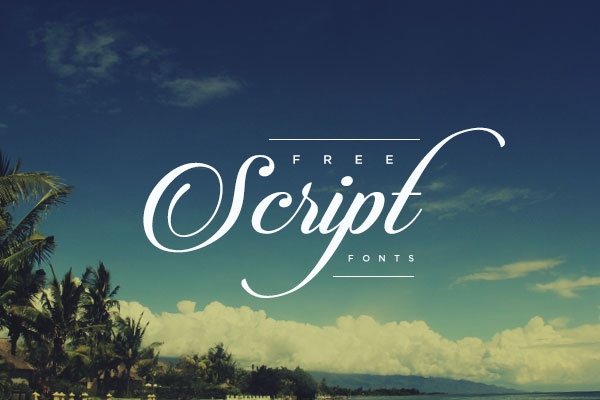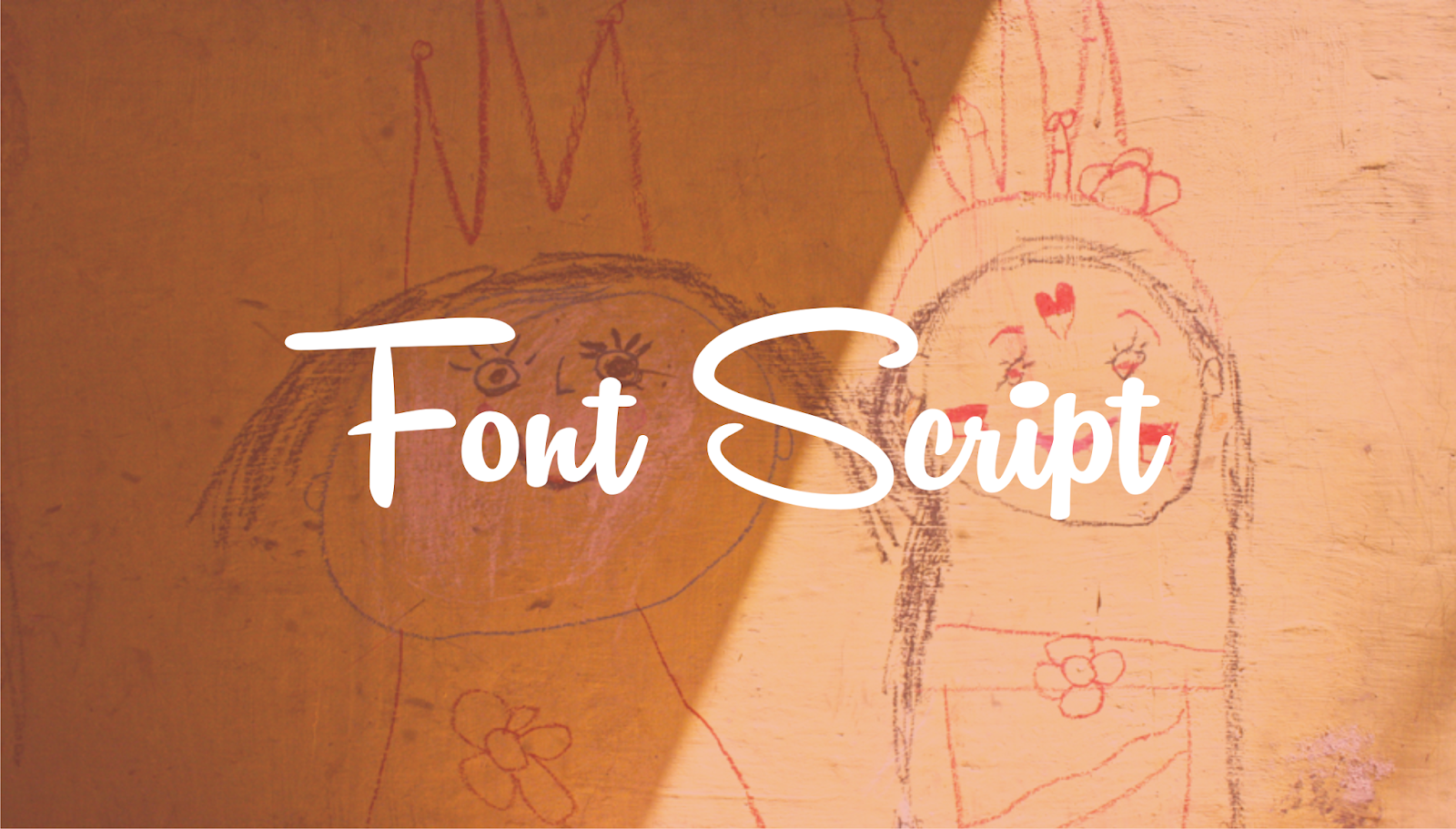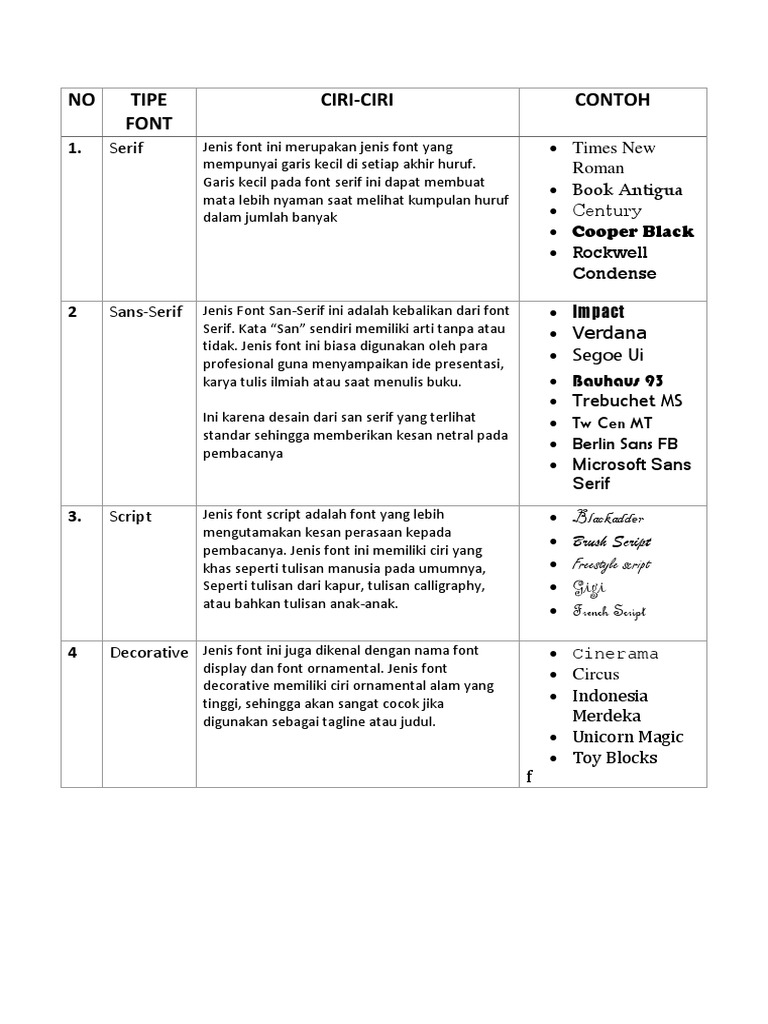
Free Typeface Gothic Merupakan Jenis Font Free Typography Fonts
All Free PSD Mockups - Download Free SVG Cut FilesFont ini memiliki karakteristik huruf kapital yang tidak terlalu tinggi dan terdapat jarat pada setiap hurufnya. Contoh dari font san serif antara lain arial tahoma century gothic dan lain sebagainya. Brooklyn merupakan jenis font yang cukup simpel sederhana terlihat bersih dan teratur.
typeface gothic merupakan jenis font
Typeface gothic merupakan jenis font. 3 script handwriting. Setelahnya anda simpan hasil foto tersebut berupa jpg jpeg atau png. Font secara sederhana typeface bisa disebut sebagai entitas yakni perwajahan karakteristik keunikan dan perbedaan yang terbentuk didalam rancangan karakter huruf. Unduh hari ini untuk mendapatkan akses ke paket lengkap huruf dan angka.
Typeface merupakan perwajahan yang membentuk karakteristik suatu kumpulan huruf sehingga membedakannya dengan jenis huruf yang lain. Font gothic secara alami akan menarik audien anda dengan hiasan dan rasa kemegahan. Font gratis jabrin oleh frida medrano biar kan melakukan trick nya. Jenis font san serif merupakan kebalikan dari jenis font serif.
Ada sesuatu yang membuat gaya font gothic ini menjadi font yang sempurna untuk tema horor. Font serif adalah jenis tipografi yang terdiri dari garis dengan tanda guratan kecil yang mudah dibaca. Serif merupakan font asli huruf alfabet latin. Banyak orang menggunakan font ini untuk keperluan desain yang tidak terlalu rumit.
Garamond merupakan jenis typeface serif berarti font dalam garamond memiliki kait. Akan kurang cocok kalau kamu menggunakan jenis font racing atau font tribal maupun gothic. Stoked adalah jenis huruf serif yang dirancang oleh marie michelle dupuis. Sang desainer mengatakan bahwa font ini diselamatkan dengan cinta setelah penolakan lima logo huruf kustom.
Begitu pula dengan stroke atau garis pada garamaond memiliki karakteristik tersendiri. Making the web more beautiful fast and open through great typography. Nah berikut 17 jenis font dasar untuk desain yang perlu kamu ketahui. Pastikan anda memotret dengan jelas dan hanya font nya saja.
Font script atau handwriting adalah jenis font yang lebih nampak natural dan elegan. Misalnya anda tertarik dengan jenis font pada brosur nah anda bisa memotret jenis font yang ada di brosur. Ini berarti jenis font serif adalah jenis font yang tidak memiliki busur elit atau goresan kecil pada setiap akhir hurufnya. Jenis jenis font san serif.
Namun sebelumnya kami sarankan untuk memotret jenis font yang ingin anda ketahui. Salah satu ciri yang mencolok dari font script atau handwriting ini adalah seperti tulisan tangan dan kaligrafi. Pada saat mahasiswa menggambarkan garamond mereka harus mencermati bentuk kait yang jika dilihat lebih dekat memiliki sudut tetapi dilihat jarak jauh seperti meruncing. Kata san sendiri memiliki arti tanpa atau tidak.